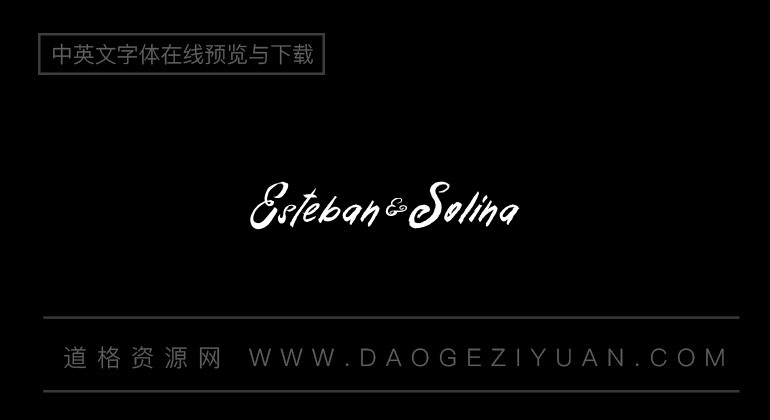
Esteban&Solina
Esteban & Solina 是一款精美的手写风格字体,由 Type Type 设计公司制作。这个字体的设计灵感来自于手写信件和手绘艺术,其笔画流畅自然,具有良好的可读性和识别度,使其成为多种设计项目的理想选择。 这个字体家族包含了多种字重和样式,包括正常、粗体、斜体、粗斜体、轮廓等样式,以及多种语言支持。Esteban & Solina 的设计风格增加了独特的个性和温暖感,适用于广泛的设计场景,如品牌标志、海报、包装等等。
Esteban&Solina是一款非常不错的手写艺术字体,具有很好的视觉感,适合于文化类的宣传设计、商业类品牌的广告和产品包装设计以及个性化文字排版等较多场景。